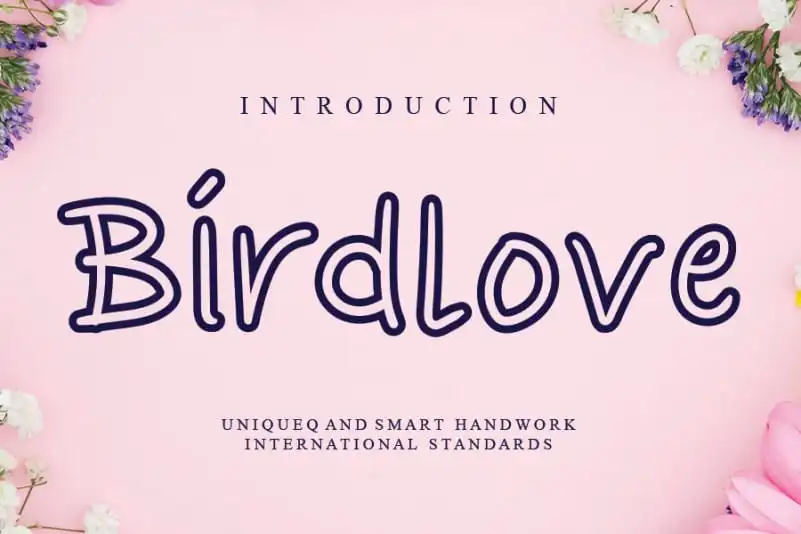
Birdlove Script Font – Download Grátis
A fonte ‘Birdlove Script Font’ é uma escolha perfeita para aqueles que buscam adicionar uma pitada de arte na tipografia dos seus projetos digitais. Desenvolvida pelo designer andikastudio, essa fonte script está repleta de personalidade e elegância, combinando elementos criativos em um formato fluido e vibrante. Com suas linhas suaves e riscos interessantes, esta fonte é ideal para criações que desejam uma identidade visual única. Ela oferece a oportunidade de transformar qualquer projeto digital em um verdadeiro trabalho de arte, seja ele uma imagem profissional de empresa ou o layout de uma página web atraente. Seja você designer gráfico ou criador de conteúdo, ‘Birdlove Script Font’ é um recurso indispensável que permitirá expressar sua personalidade e habilidades de design através do texto. Sua aplicação será inovadora e impactante em qualquer projeto, tornando-a uma escolha óbvia para aqueles buscando dar um toque especial a seus materiais digitais.